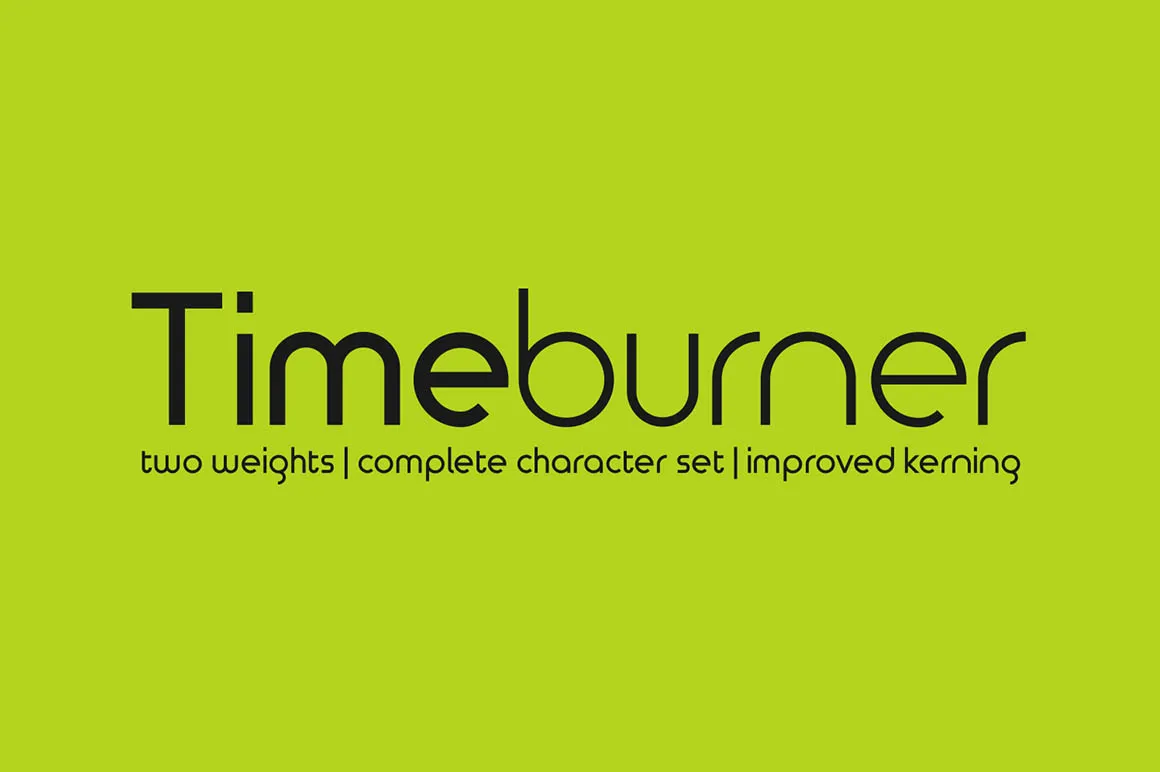
Timeburner Font
A fonte Timeburner é uma escolha perfeita para projetos modernos e criativos na categoria sans serif. Desenvolvida por Hamilton, ela traz um visual limpo e distinto, muito atraente tanto online quanto impresso. Esta fonte é ideal para iniciantes devido à sua simplicidade geometricamente básica, mas rapidamente se mostrou uma opção valiosa com muitas milhares de downloads em múltiplos projetos na web. Hamilton ainda continuou trabalhando e atualizando a fonte com duas pesos diferentes e um conjunto de caracteres mais completo para responder às necessidades dos usuários que querem adicionar diacriticos. Embora a originalidade inicial da font contasse com apenas os caracteres básicos, isso não impediu ela de se tornar uma fonte popular. A evolução continuada faz dela uma opção versátil e adaptável para diversos projetos gráficos.